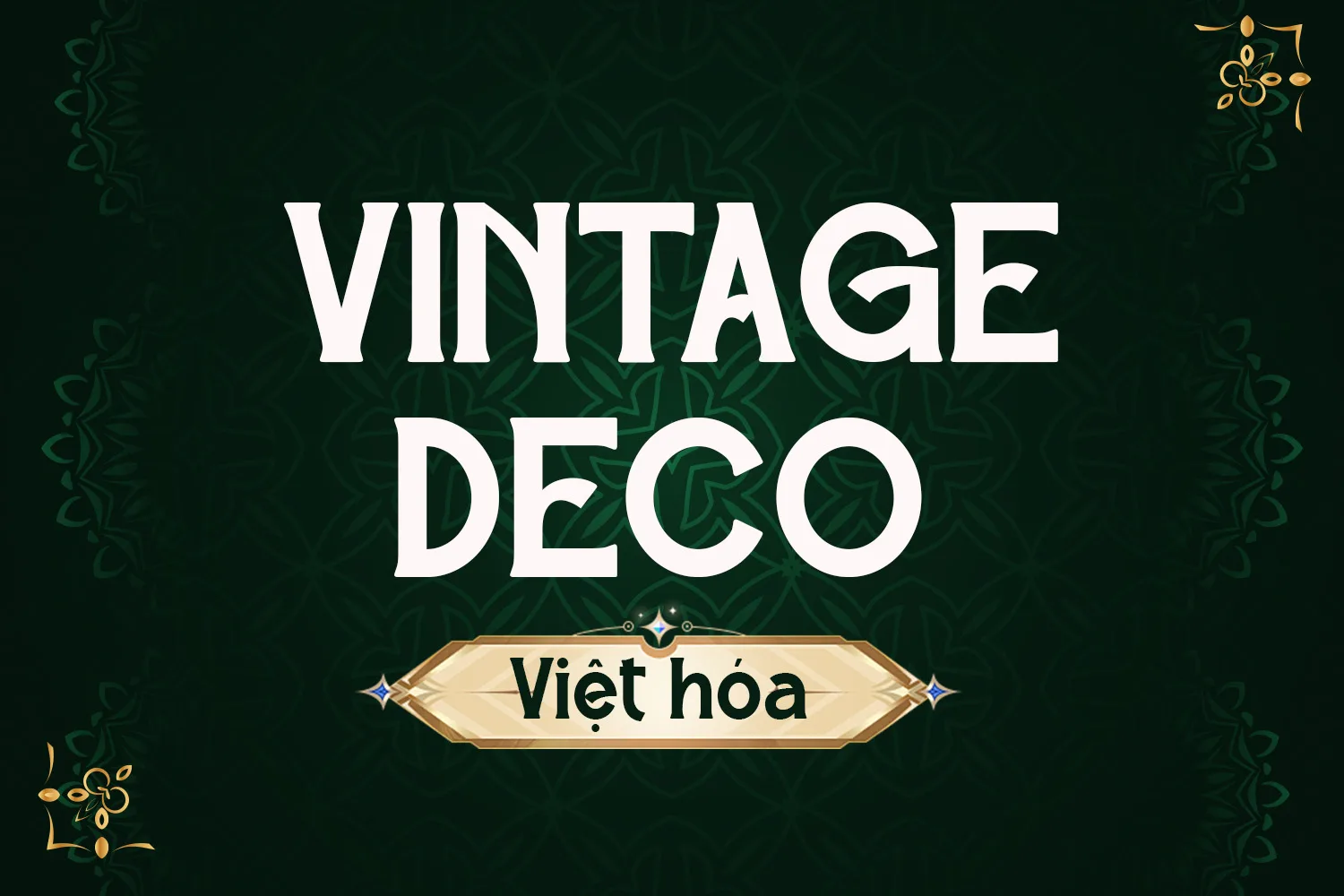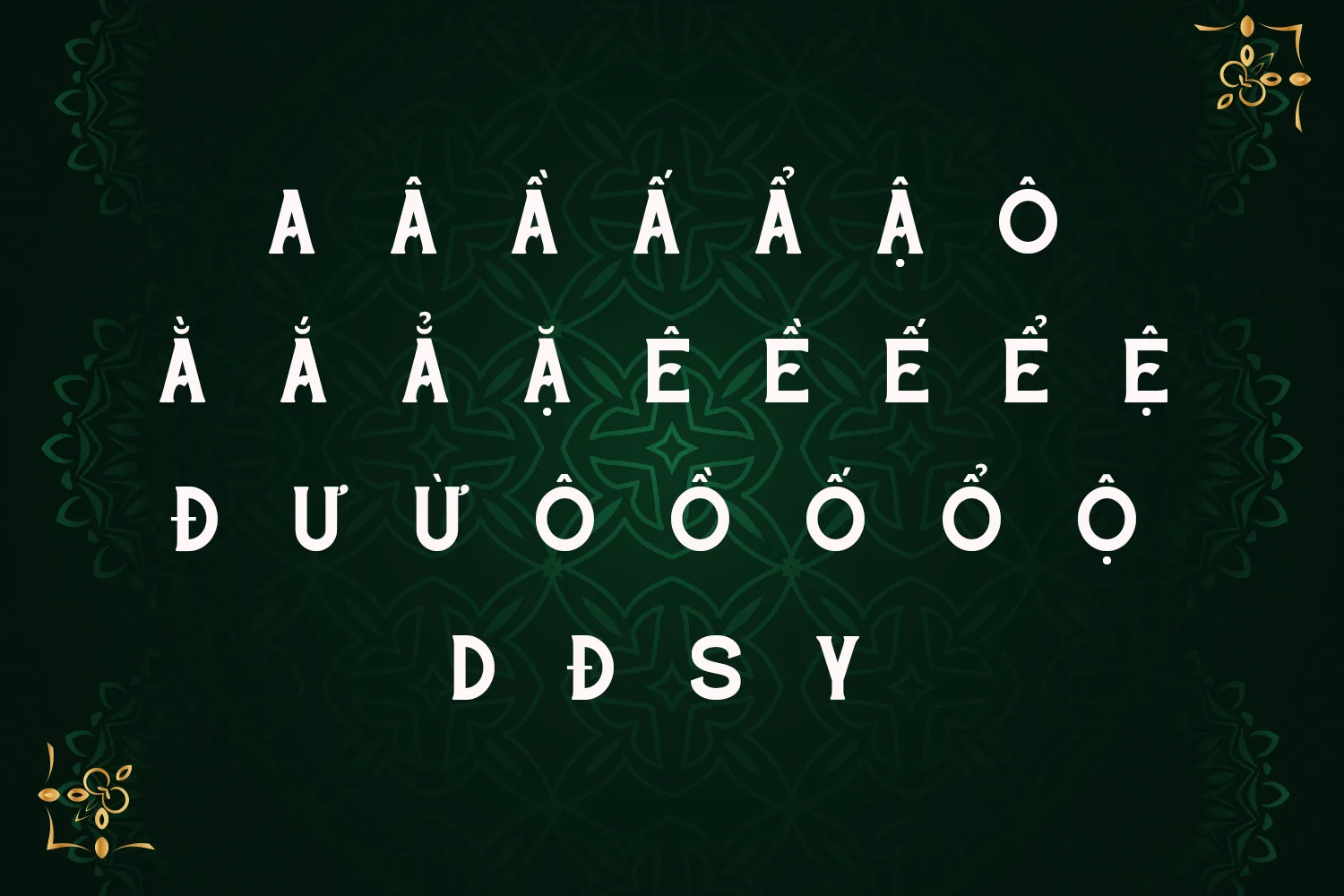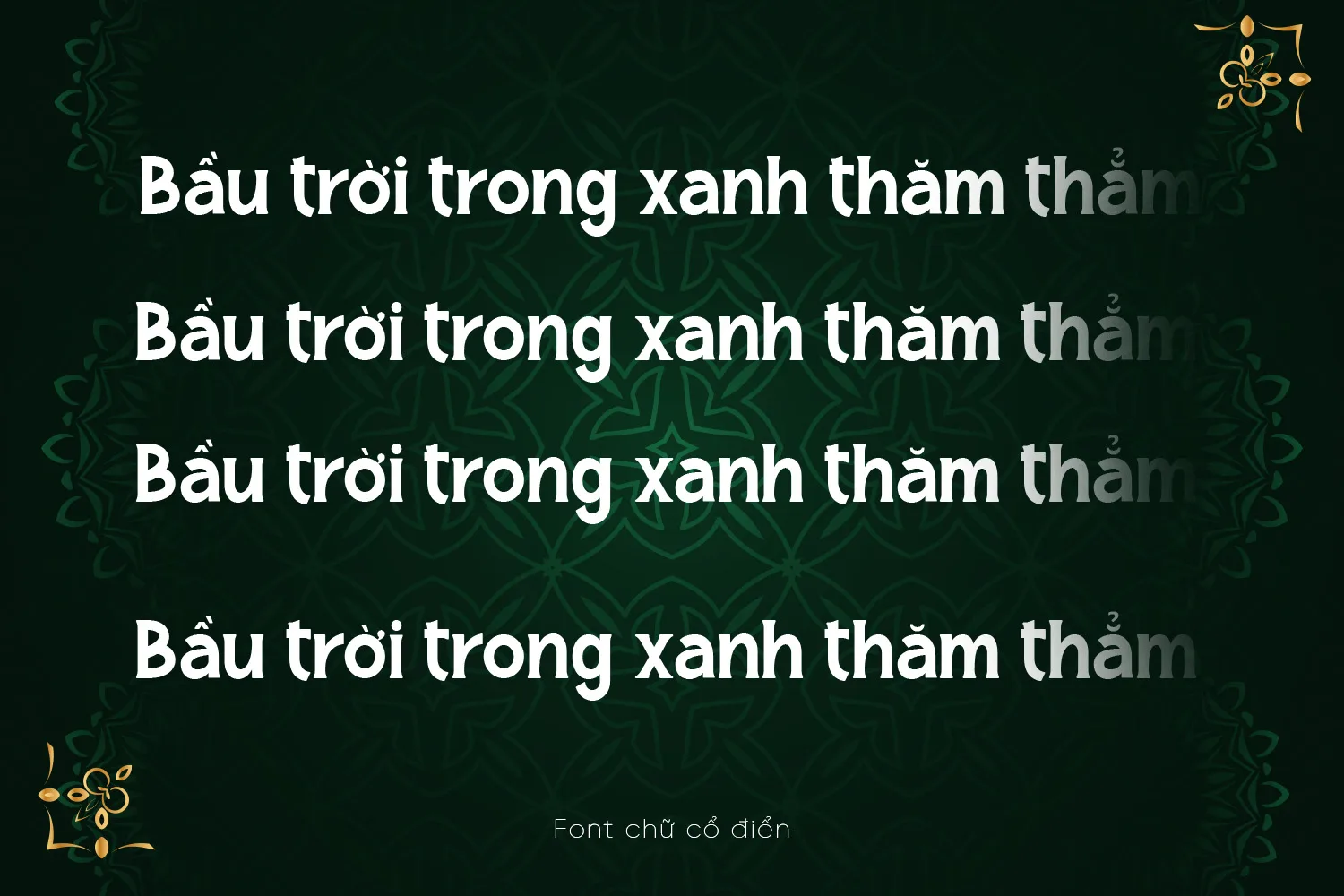
DVN Vintage Deco – Font chữ phong cách hoài cổ với dấu ấn Art Deco đầy cá tính
DVN Vintage Deco Việt hóa là một kiểu chữ lấy cảm hứng từ phong cách Art Deco – biểu tượng thị giác của sự sang trọng và hiện đại trong thập niên 1920–1940. Với những đường nét hình học chắc chắn, phần đầu chữ được cách điệu tinh tế cùng loạt ligature độc đáo, font mang lại cảm giác cổ điển nhưng vẫn hiện đại. Bộ font hỗ trợ đầy đủ tiếng Việt, đi kèm với chữ hoa – chữ thường, số học và hệ thống ký tự mở rộng đa ngôn ngữ. Phù hợp cho các thiết kế poster, bìa sách, tiêu đề, thương hiệu mang phong cách retro, cổ điển hoặc nghệ thuật thị giác ấn tượng. DVN Vintage Deco không chỉ là một bộ font, mà còn là một chuyến du hành thị giác về thời kỳ vàng son của mỹ thuật trang trí.